Đây là
bộ font MTD Việt Hóa cực đẹp, có chứa rất nhiều font chữ Script Việt hóa với nhiều phong cách khác nhau rất phù hợp để làm typography cho các video âm nhạc Youtube, banner quảng cáo và nhiều loại hình thiết kế khác.
Demo một số hình ảnh sử dụng bộ font này:
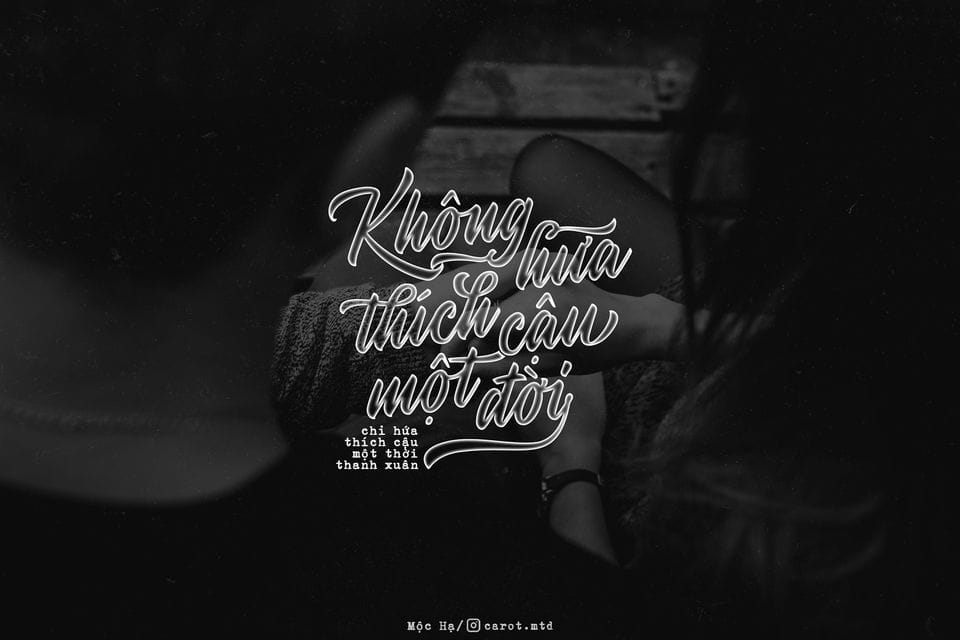
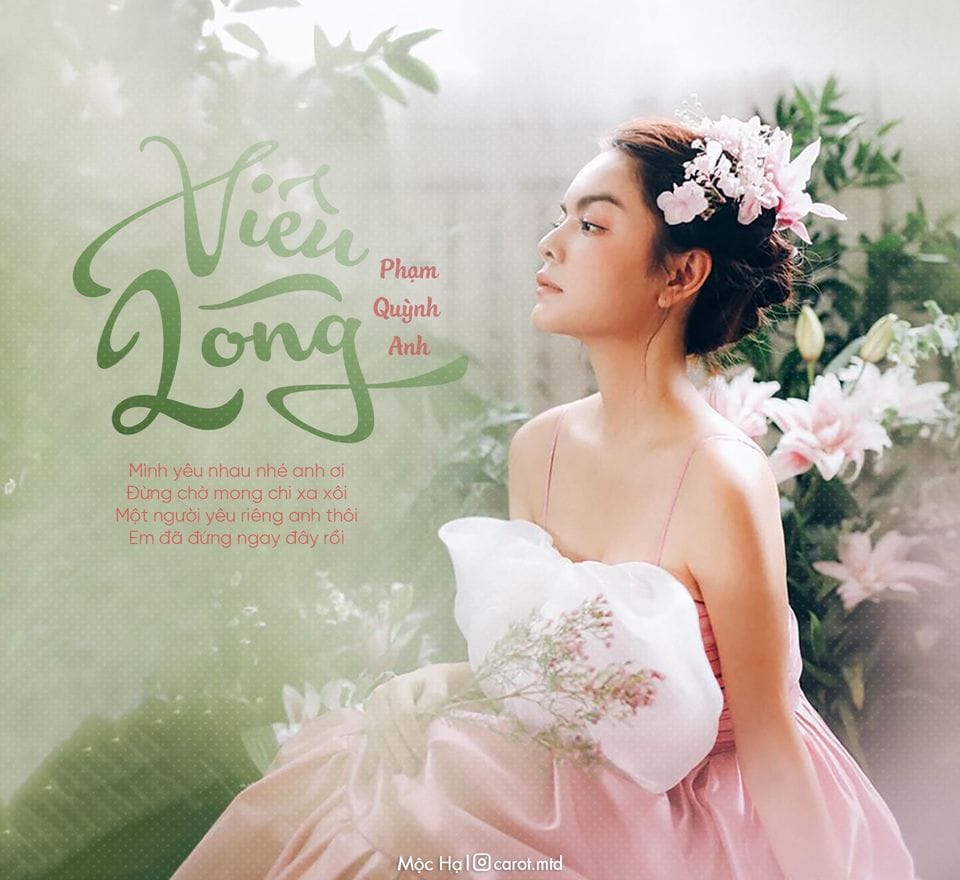
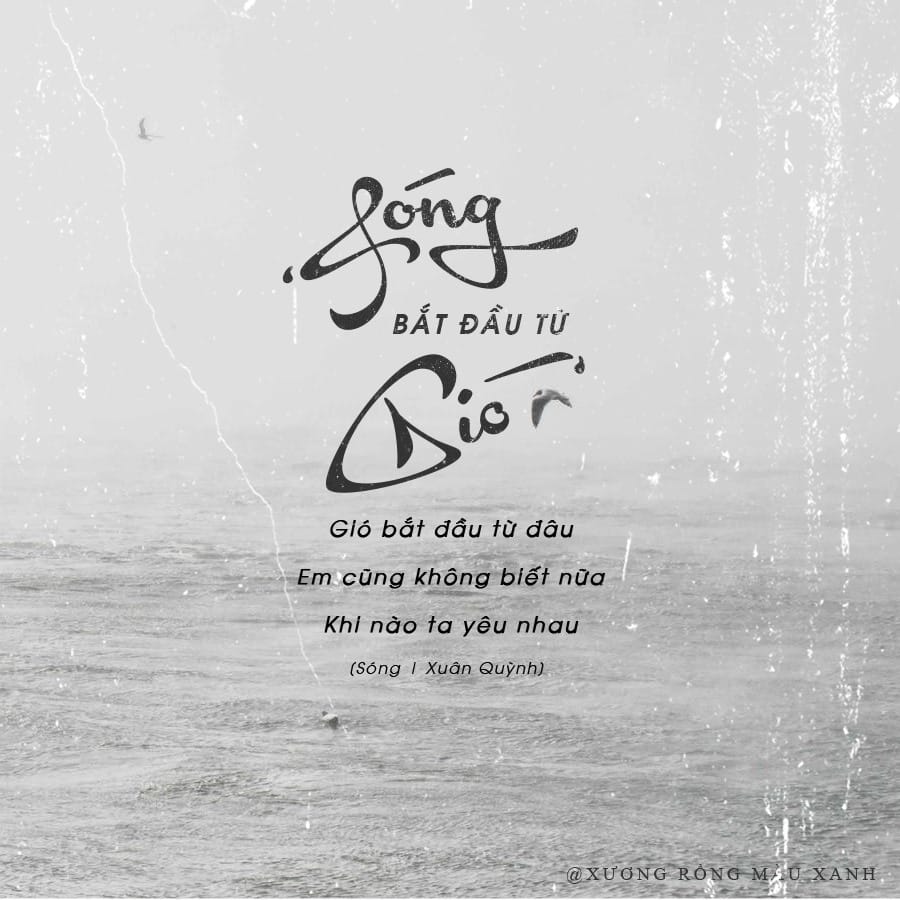
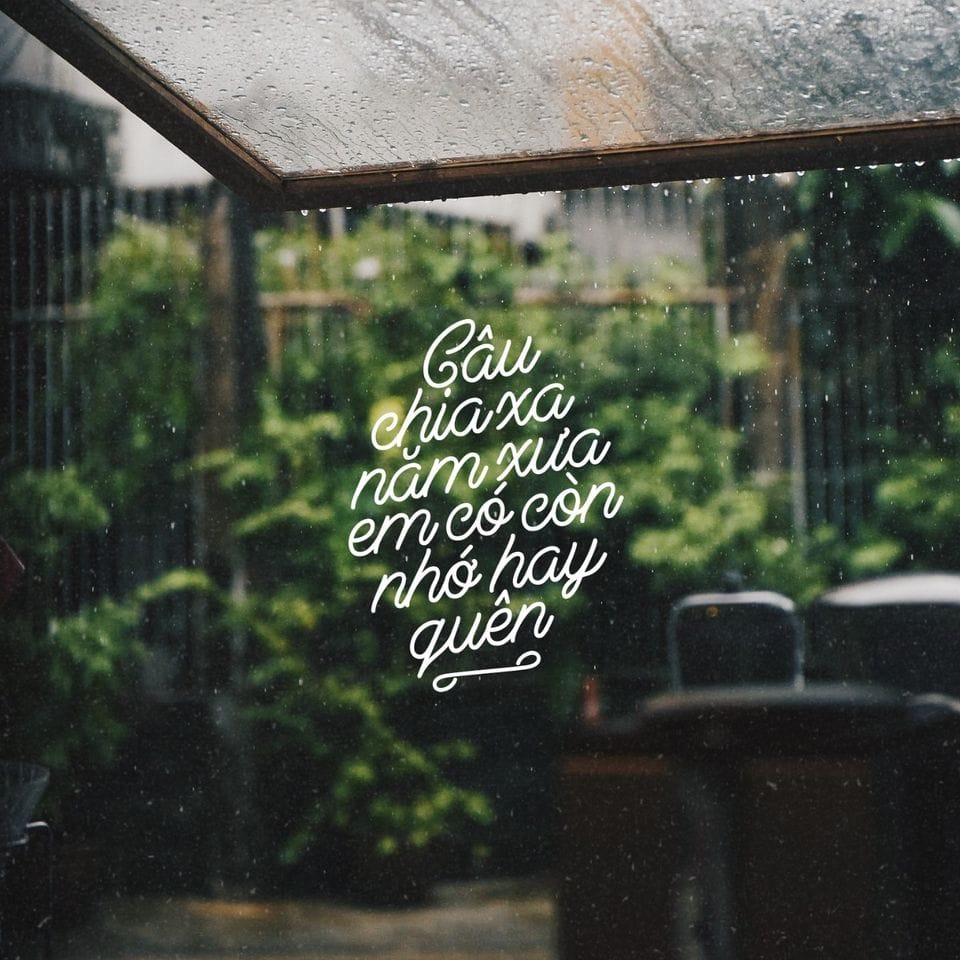
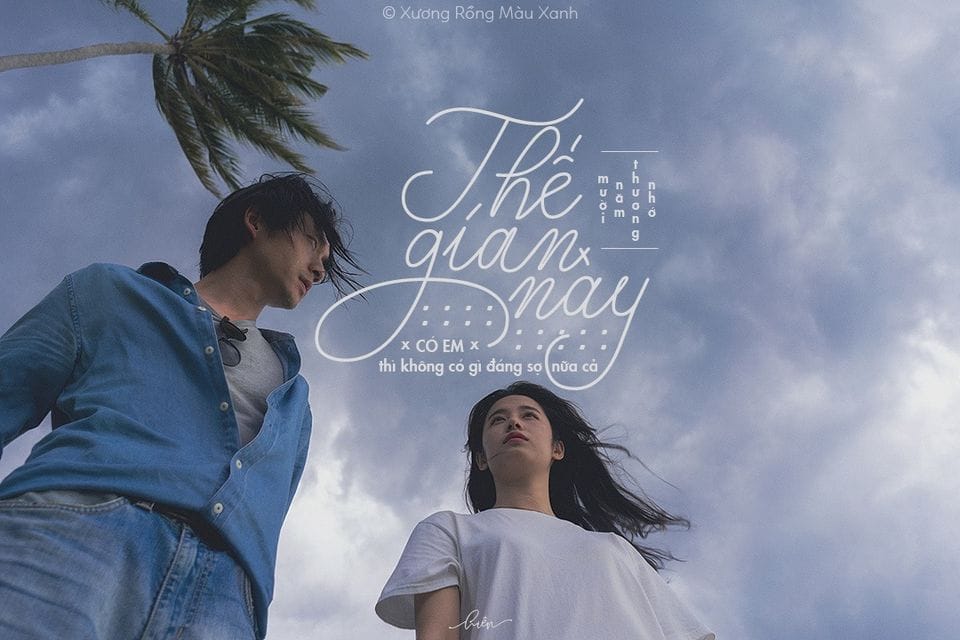
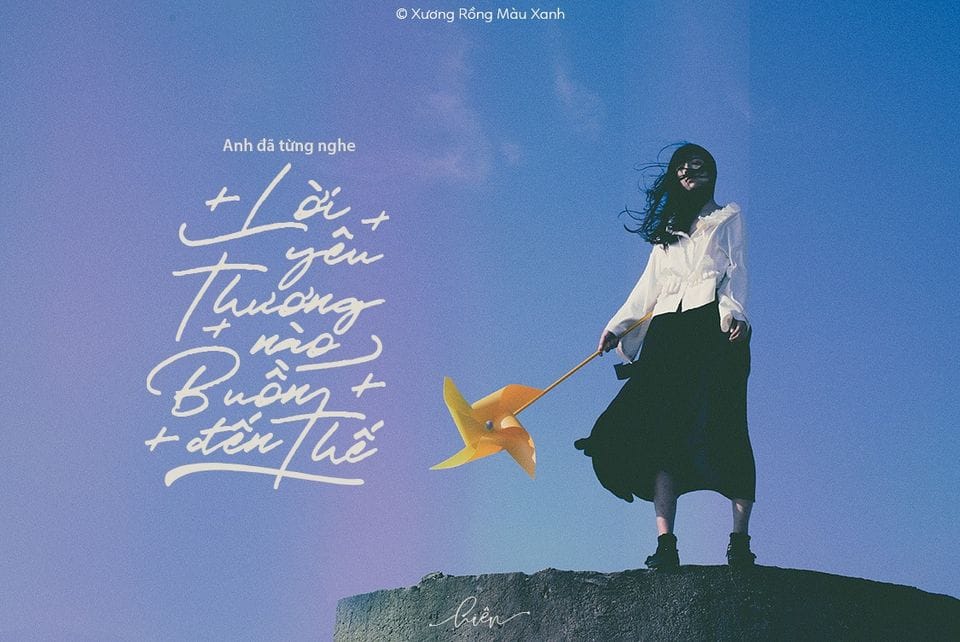
- MTD Abbassy Script
- MTD Carrington
- MTD Daytonia
- MTD Elodie
- MTD Lazy Ride Script
- MTD Loveletter No.9
- MTD Maryatha
- MTD Nettizen Script Dancing
- MTD Retrology Block
- MTD Youther Script
- MTD Autogate Stamp
- MTD Briliants Typeface
- MTD Fashion Vogue
- MTD Hillstown Aged
- MTD Hillstown Clean
- MTD Oops
- MTD Orangimelo
- MTD Ramblin Paint
- MTD Red Bright
- MTD ShimesOne
- MTD The Beautyline
- MTD The Duality
- MTD Acryle Script
- MTD AlFresco
- MTD Anydore
- MTD Authentica Rough
- MTD Berliana Monoline
- MTD Charlize One
- MTD Hangbird
- MTD Hijrnotes
- MTD Himalaya Sans Serif
- MTD Himalaya
- MTD Houstoner Script
- MTD JV Signature Regular
- MTD Mind Blowing Light
- MTD One Starry Night
- MTD Portrait Script Bounce
- MTD Prida 01 Black
- MTD Prida 01 Bold
- MTD Prida 01 Light
- MTD Prida 01
- MTD Prida 02 Calt